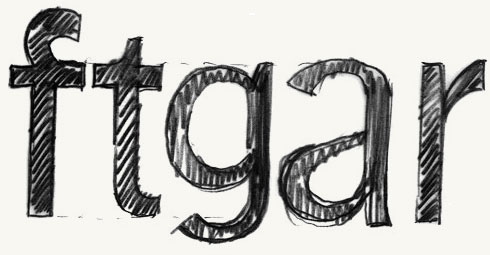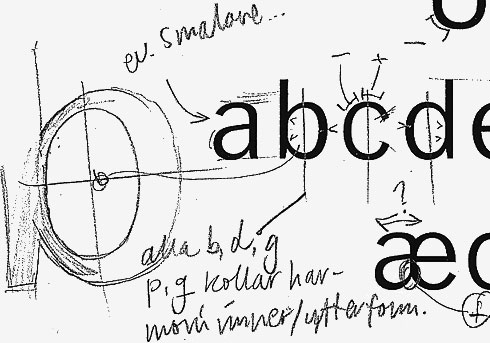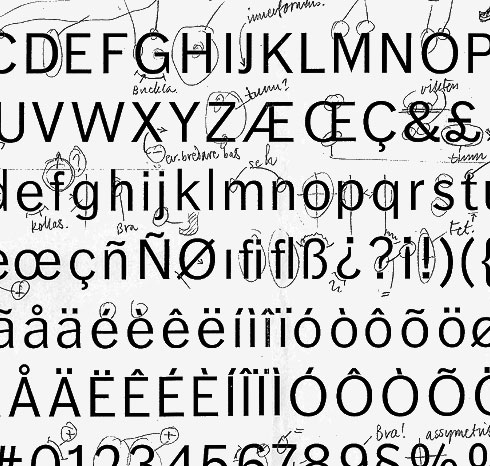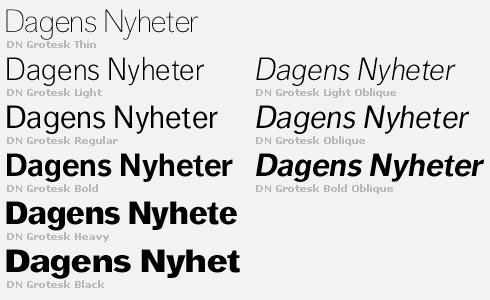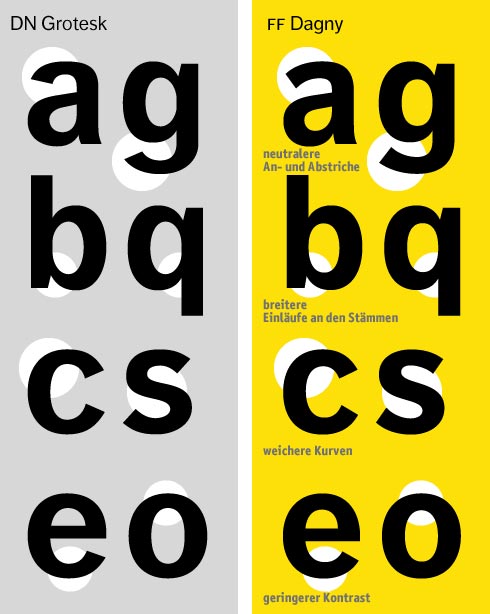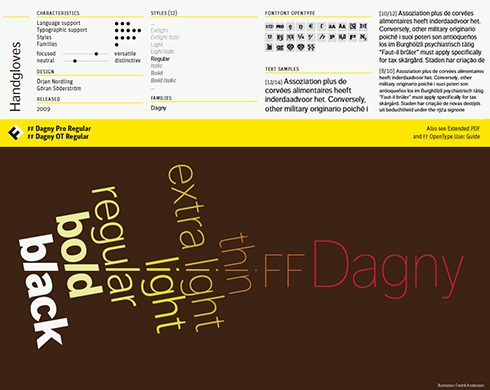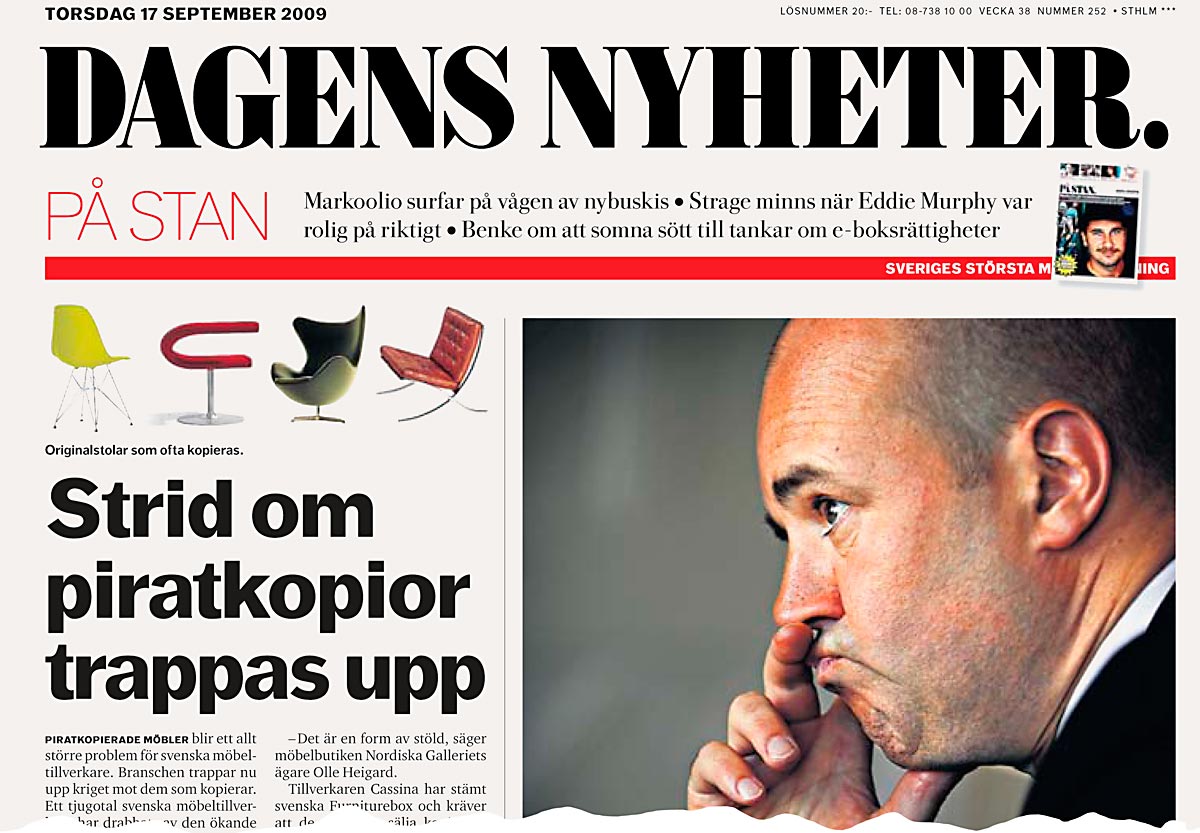
Der 4. Teil und letzte unserer FontFont-Neuvorstellungen* widmet sich FF Dagny, die ursprünglich für die größte Schwedische Morgenzeitung Dagens Nyheter (»Nachrichten des Tages«) entwickelt wurde. Wie sie entstand, warum sie heute anders aussieht und wo es den kostenlosen OpenType-Probierfont FF Dagny Thin gibt … alles in diesem Beitrag.
Die Geburtsstunde der FF Dagny geht zurück ins Jahr 2002, als sich Dagens Nyheter dazu entschloss, vom Nordischen Format zum kleineren Tabloid-Format zu wechseln. Die liberale »DN« wurde 1864 von Rudolf Wall mit der Unterstützung des Verlegers Albert Bonnier gegründet und ist noch heute Eigentum der Medien-Familie Bonnier.
Die Verkleinerung des Layouts, betreut von Bark Design, hatte unmittelbare Folgen für die Redakteure, das Rektorat und die Typografie. Nur zwei Jahre zuvor erlebte DN das letzte Redesign, betreut von dem erfahrenen Mario R. García (García Media) – Besucher der TYPO-Konferenz kennen ihn als charmanten Redner. Bei diesem Projekt lernte García auch den schwedischen Schriftentwerfer Örjan Nordling kennen, Kreativdirektor von Pangea Design in Stockholm, der bereits seit 1996 für Dagens Nyheter arbeitete. Nachdem sie die Aufgaben für eine neue, robuste Zeitungsschrift definiert hatten, schuf Nordling 1999 die DN Bodoni, exklusiv für die Stockholmer Zeitung.
Auch 2002 wurde Pangea in das Redesign für das Tabloid-Format eingebunden. Die neue kompakte Gestaltung erforderte eine robuste, platzsparende Schrift, sicherlich eine Sansserif – der Anstoß für die Entwicklung der DN Grotesk.
Das Pangea-Design-Team mit Örjan Nordling (links) und Göran Söderström (Mitte) prüft mit Fredrik Anderson (Dagens Nyheter) erste Probedrucke von DN Grotesk
Die Verwendung serifenloser Schriften auf den Seiten von Dagens Nyheter hat in den vergangenen 20 Jahren kontinuierlich zugenommen. Meist war es die Akzidenz Grotesk, zunächst in Verbindung mit Bauer Bodoni (bis 1996), danach Berthold Bodoni (1997–2000) und später die hauseigene DN Bodoni. Die DN Grotesk, deren Mittellänge mit der von DN Bodoni übereinstimmt, wird bis heute für Überschriften, Sublines und Introtexte eingesetzt. Verantwortlich für den Ausbau der Familie waren zwei Designer, nämlich Örjan Nordling und Göran Söderström.
Örjan Nördling, geboren 1958, studierte zunächst an der »Konstfack« in Stockholm, danach an der Schule für Gestaltung Basel (1983–85). Nach der Gründung von Pangea Design spezialisierte er sich auf die Entwicklung von Corporate Schriften. 2004 erhielt er den Berling Preis für seine Berling Nova. Göran Söderström, geboren 1974, ist Schriftentwerfer (Autodidakt) und Font-Entwickler. Seit 2007 arbeitete er bei Pangea Design. Den größten Teil seiner Freizeit verbringt er mit dem Entwerfen eigener Schriften (zum Beispiel die kuriose Metall-Script Flieger Pro).
Links: Specimen Book, Printing Types H.W. Caslon & Co., Ltd, London, 1902: Doric No. 6 60 pt, 48 pt, 42 pt, 36 pt, 30 pt; Rechts: Wilhelm Woellmer’s Schriftgießerei, Berlin, 1926: Halbfette Consul 1, klassische Form No 1788 – No 1799
Die Wurzeln der FF Dagny reichen freilich weiter zurück als ins Jahr 2002. Tatsächlich ist sie von Schriftproben aus den 1920er Jahren beeinflusst, unter anderem von den Gießereien Caslon and Son, Wilhelm Woellmer und Proben aus der Dagens-Nyheter-Hausdruckerei. Das Design-Team wollte eine Schrift mit stärkerem Kontrast, dynamischeren Konturen und eine großen Mittellänge. Doric Grotesk brachte alle diese Eigenschaften mit sich. Sie kam einst bei der britischen Gießerei Stephenson Blake heraus und basierte auf einer frühen Sansserif von William Caslon IV, der 1816 zum ersten mal serifenlose Buchstabenformen zu Schriftfamilien ausbaute. Mit ihren kräftigen, fast fetten Versalien, einheitlich spationierten Gemeinen und der großer Mittellänge ist die Schrift ideal für widrige Druckbedingungen und klein gesetzte Texte, zum Beispiel Kleinanzeigen in Tageszeitungen.
Eine andere Inspirationsquelle war Consul Grotesk der Gießerei Woellmer, die – gemeinsam mit anderen deutschen Schriften – gerne in schwedischen Verlagen eingesetzt wurde. Die Schrift lieferte einige Ideen für Details, mit der die neue DN-Sansserif eigenständig und unverwechselbar werden konnte, zum Beispiel das kleine f mit seiner zurückgelehnten Bogen, die charakteristischen g und b sowie die »kursivischen« An- und Abstriche bei a, c, e und s.
Erste Bleistiftzeichnungen der DN Grotesk, später FF Dagny, dienten dazu, die Design-Richtung der Schrift festzulegen. Das f mit dem gekrümmten Rücken ist schon dabei, wie auch der »kursivische« Anstrich beim a und das charakteristische hochstehende g.
Ein erster Probesatz der DN Grotesk mit Anmerkungen und Korrekturvorschlägen
Ungezählte Verbesserungsvorschläge auf einem Korrekturbogen während der Entwicklung der DN Grotesk
Die gesamte DN-Grotesk-Familie des Jahres 2002 im Überblick
Am Ende flossen verschiedene Ideen aller historischer Vorlagen in die Entwicklung der DN Grotesk ein. Dabei ist es Örjan Nordling und Göran Söderström gelungen, eine harmonische Familie aufzubauen. Ein besonderes Merkmal der DN Grotesk ist die große Mittellänge, die rund 10 % über der von Akzidenz Grotesk liegt. Sie garantiert, dass die Schrift auch in kleinen Graden groß wirkt und gut lesbar bleibt. In der allgemeinen Anmutung ergibt sich eine leicht-schmale Schrift mit offenen Buchstabenformen. Auch die Ober- und Unterlängen sind knapp bemessen, so dass die Zeilen enger gesetzt werden können. Die kursiven Schnitte – eigentlich nur schräg gestellt Grundformen – wurden selten in Dagens Nyheter eingesetzt.
Zur Schrift: ugly und das f geht mal garnicht.